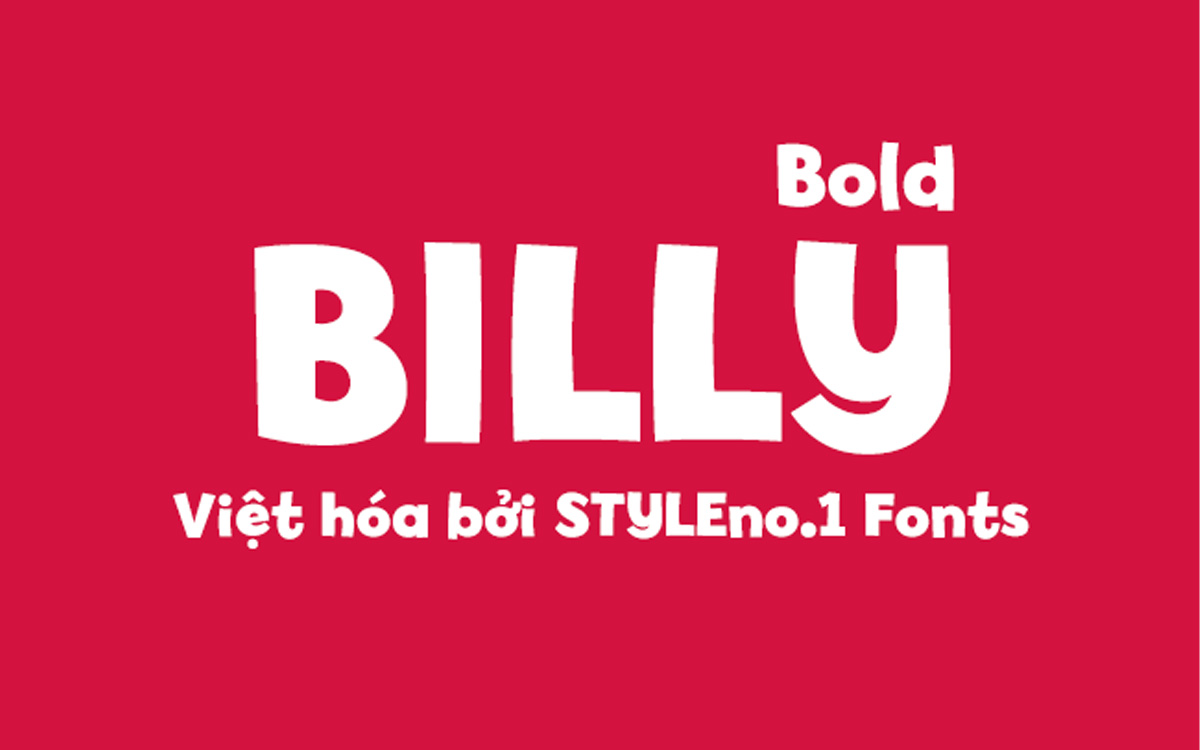
Trong thế giới thiết kế đồ họa hiện đại, phông chữ không chỉ đơn thuần là công cụ hiển thị văn bản mà còn là thần thái, là linh hồn truyền tải cảm xúc của toàn bộ ấn phẩm truyền thông. Nếu bạn đang tìm kiếm một làn gió mới tràn đầy năng lượng tích cực, sự ngây thơ và nét ngộ nghĩnh đặc trưng thì SVN-Billy Bold chính là câu trả lời hoàn hảo nhất. Với cấu trúc nét chữ mập mạp, bo tròn quyến rũ và biểu cảm vui tươi, font chữ này đang trở thành sự lựa chọn hàng đầu của các nhà thiết kế chuyên nghiệp trên toàn quốc.
Dù bạn đang thực hiện dự án truyền thông cho ngành hàng trẻ em, xây dựng hình ảnh thương hiệu ẩm thực độc đáo hay sáng tạo các ấn phẩm mạng xã hội mang phong cách cute, SVN-Billy Bold đều có khả năng biến những ý tưởng đơn giản trở nên sinh động và thu hút thị giác một cách kỳ diệu. Hãy cùng khám phá chi tiết về bộ font chữ độc đáo này cũng như lý do vì sao nó lại tạo nên cơn sốt trong cộng đồng designer thời gian qua.
Font Chữ Vui Vẻ, Dễ Thương, Hoạt Hình SVN-Billy Bold – Lựa Chọn Hàng Đầu Cho Lĩnh Vực Trẻ Em, Đồ Ăn Food Và Style Cute
Sự xuất hiện của bộ font chữ SVN-Billy Bold đã giải quyết triệt để bài toán tìm kiếm nét chữ vừa có độ nặng thị giác tốt (Bold) vừa giữ được tính chất mềm mại, tinh nghịch. Được thiết kế theo phong cách hoạt hình (cartoon style), font chữ này giải phóng bản thân khỏi những quy tắc hình học cứng nhắc để mang đến các đường nét tự nhiên, ngẫu hứng nhưng vô cùng hài hòa.
Từ góc độ tâm lý học màu sắc và hình khối trong tiếp thị, những hình dạng bo tròn như SVN-Billy Bold có khả năng kích hoạt phản ứng tâm lý tích cực, tạo cảm giác an toàn, gần gũi và vui vẻ cho người xem. Đây chính là “vũ khí bí mật” giúp các chiến dịch quảng cáo nhắm vào đối tượng thiếu nhi và giới trẻ đạt được tỷ lệ chuyển đổi vô cùng ấn tượng.
1. Phong Cách Phông Chữ Bo Tròn Vui Nhộn, Mang Lại Cảm Giác Dễ Thương Ngay Từ Ánh Nhìn Đầu Tiên
SVN-Billy Bold gây ấn tượng mạnh nhờ vào các đường nét bo tròn đầy đặn, không chứa các góc nhọn sắc nét hay đường thẳng cứng nhắc. Cấu trúc chữ mập mạp kết hợp cùng các khoảng hở (counters) được tinh chỉnh hợp lý tạo nên một tổng thể vô cùng dễ thương, đậm chất hoạt hình Disney hay các bộ phim hoạt hình hiện đại.
Mỗi ký tự trong SVN-Billy Bold như đang chuyển động và nhảy múa, mang đến nguồn năng lượng tích cực cho thiết kế. Điểm đặc biệt là dù sở hữu nét chữ dày và đậm, font chữ vẫn giữ được sự thoát nét, không gây cảm giác nặng nề hay ngột ngạt khi áp dụng vào các tiêu đề chính (Headlines) hoặc các đoạn slogan ngắn.
- Nét chữ dày dặn: Giúp các dòng tiêu đề nổi bật rực rỡ trên mọi nền chất liệu hoặc hình ảnh phức tạp.
- Đường cong mềm mại: Loại bỏ sự thô cứng, mang lại cảm giác thân thiện, dễ tiếp cận cho người xem ở mọi lứa tuổi.
- Nhịp điệu chữ ngẫu hứng: Tạo cảm giác tự nhiên như nét vẽ tay của các họa sĩ hoạt hình chuyên nghiệp.
2. Ứng Dụng Hoàn Hảo Trong Lĩnh Vực Sản Phẩm Và Giáo Dục Trẻ Em
Đối tượng trẻ nhỏ luôn bị thu hút bởi những hình ảnh rực rỡ, sinh động và các đường nét tròn trịa ngộ nghĩnh. SVN-Billy Bold được sinh ra để đáp ứng hoàn hảo mọi yêu cầu khắt khe nhất trong ngành thiết kế dành cho trẻ em. Từ các bộ sách truyện tranh, sách tô màu, bảng chữ cái thông minh cho đến bao bì đồ chơi, đồ dùng học tập, font chữ này đều phát huy tối đa sức mạnh truyền tải của mình.
Khi áp dụng SVN-Billy Bold vào các thiết kế dành cho thiếu nhi, bạn sẽ dễ dàng tạo ra một không gian trực quan đầy màu sắc kỳ diệu, kích thích trí tưởng tượng và sự tò mò của trẻ. Các trường mầm non, trung tâm anh ngữ thiếu nhi hay các khu vui chơi giải trí cũng thường xuyên ưu tiên sử dụng bộ font này trên bảng hiệu, poster sự kiện để tạo dựng hình ảnh thương hiệu thân thiện trong mắt các phụ huynh.
- Bao bì sản phẩm tã giấy, sữa, đồ chơi: Tạo niềm tin và sự yêu thích ngay từ cái nhìn đầu tiên.
- Ấn phẩm giáo dục: Giúp trẻ cảm thấy việc học tập trở nên nhẹ nhàng, vui vẻ như một trò chơi.
- Thiết kế thời trang trẻ em: In các khẩu hiệu dễ thương lên áo thun, mũ, nón hay phụ kiện thiếu nhi.
3. Sự Lựa Chọn Đột Phá Cho Ngành F&B, Menu Đồ Ăn, Food & Beverage Và Quán Trà Sữa
Trong ngành công nghiệp dịch vụ ăn uống (F&B), yếu tố cảm xúc đóng vai trò vô cùng quan trọng trong việc kích thích vị giác của khách hàng. SVN-Billy Bold với dáng vẻ tròn xinh, mập mạp thường gợi liên tưởng đến những món ăn ngon lành như bánh ngọt, kẹo dượng, kem tươi, trà sữa hay các món ăn vặt giòn rụm.
Các thương hiệu nhà hàng, quán ăn vặt, tiệm bánh bakery hay thương hiệu trà sữa hướng tới giới trẻ (Gen Z, Gen Alpha) có thể khai thác tối đa SVN-Billy Bold để làm tiêu đề menu, thiết kế bao bì hộp takeaway, ly giấy, sticker dán nhãn hoặc các bài đăng quảng cáo món mới trên Facebook, Instagram và TikTok. Nét chữ đầy đặn giúp tên món ăn trở nên vô cùng bắt mắt và “ngon miệng”.
- Menu quán trà sữa, ăn vặt: Giúp tên các món topping, trà trái cây trở nên nổi bật và thu hút mắt nhìn.
- Bao bì thực phẩm đóng gói: Thiết kế nhãn mác cho snack, kẹo, thạch trái cây, nước giải khát.